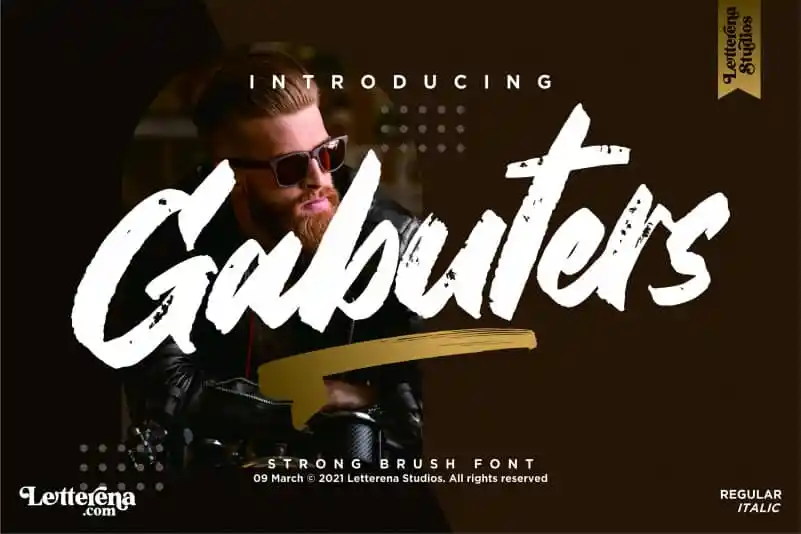
A fonte ‘Gabuters Font’ oferece uma experiência única para designers em busca de uma letra com toque suave de esferográfica que se encaixa perfeitamente em projetos variados, como logotipos e identidade visual, designs de mobiliário, embalagens de produtos, mugs personalizados, cartazes, sacolas de presente, roupas personalizadas, capas de livros, cartões de nome, convites e cartões de agradecimento, selos, fotografia, marcas de água, eventos especiais ou qualquer outro projeto onde você precise de um toque forte e sofisticado. O designer Letterenastudios criou uma fonte premium em estilo brush que é perfeitamente adaptável para seus projetos luxuosos. Seja para criar o próximo hit de design ou simplesmente dar um toque especial, Gabuters Font tem o poder de tornar seu trabalho ainda mais inovador e profissional.